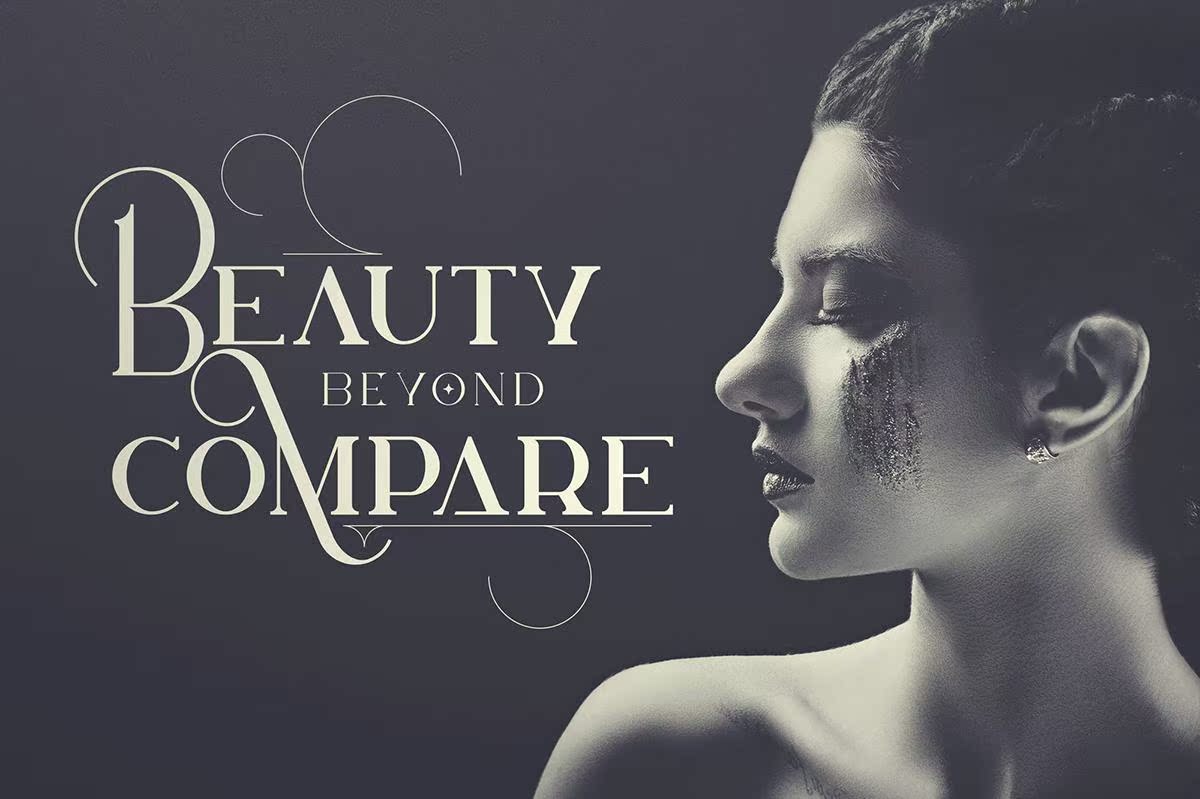
LotuseaterVintage可帮助您在几次点击中创建一个出色的Vintage Elettering或LogoTemplates。此字体简洁,带有连字、色调,可交替使用字形、装饰和多语言支持。它保存了适用于大尺寸和小尺寸的多功能性。因此,它适用于品牌项目、家居设计、产品包装、,magazineheaders.itisalSosimplyasAstylishTextOverlayAnyBackgroundImage。